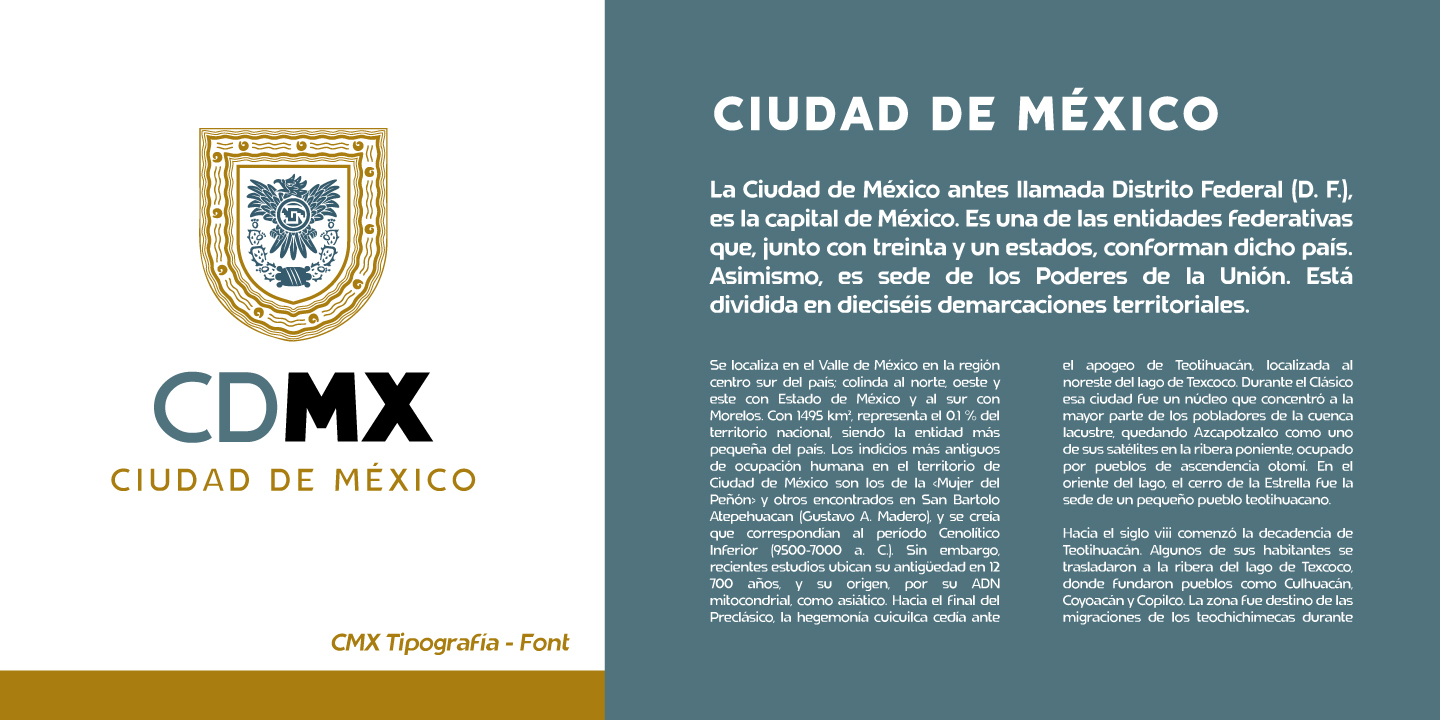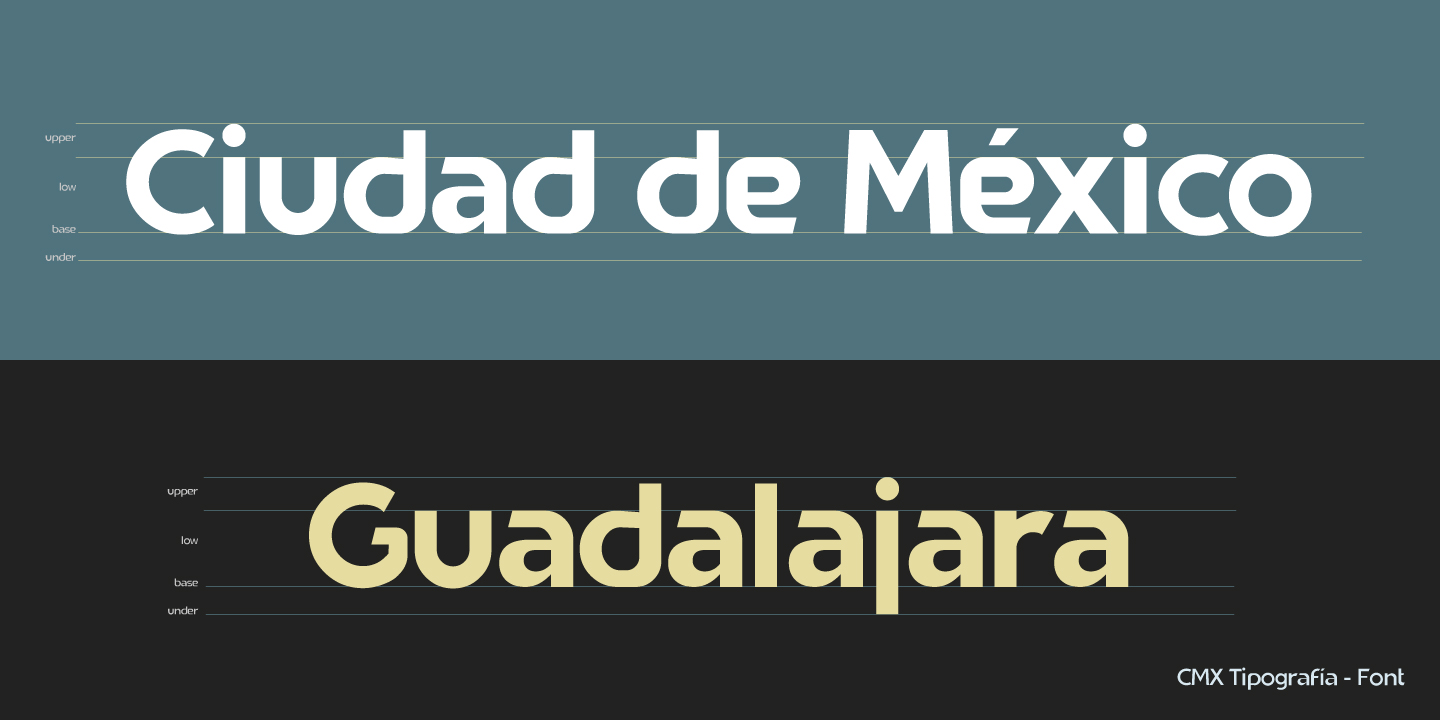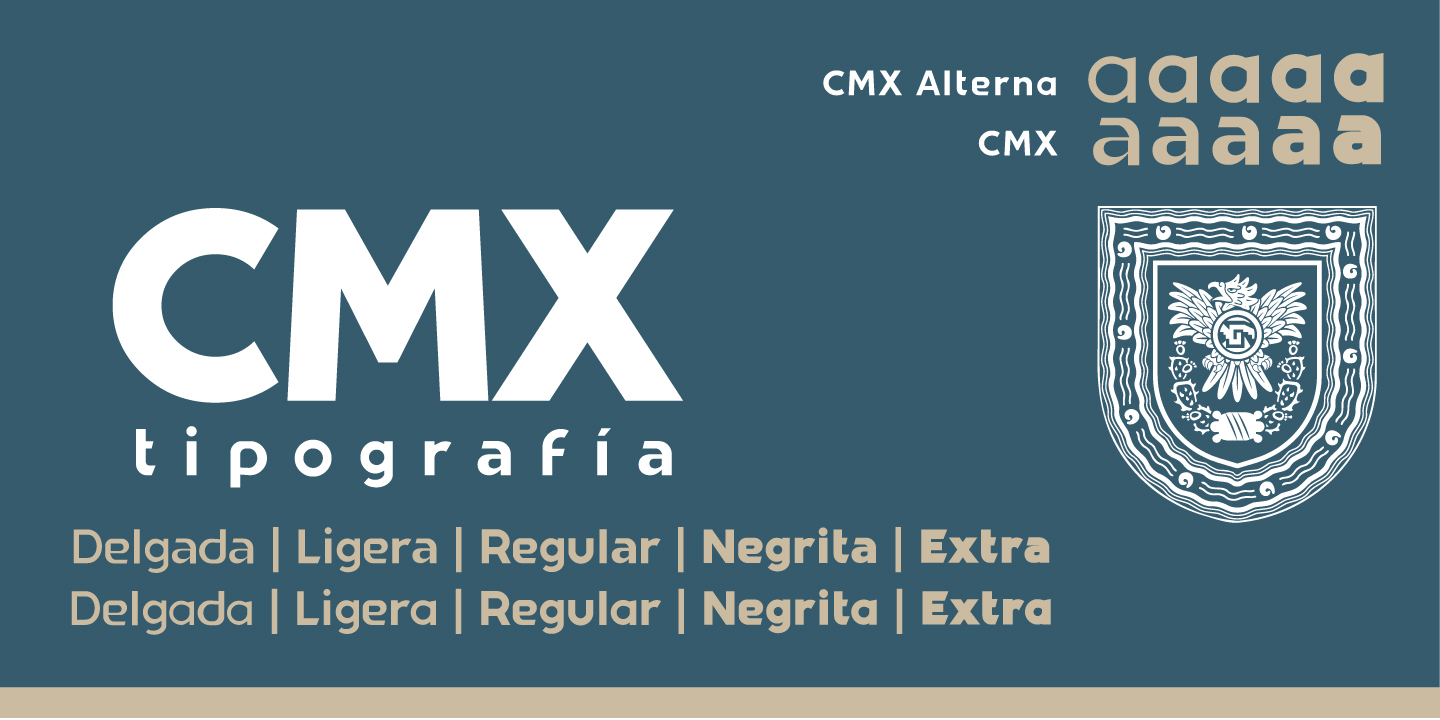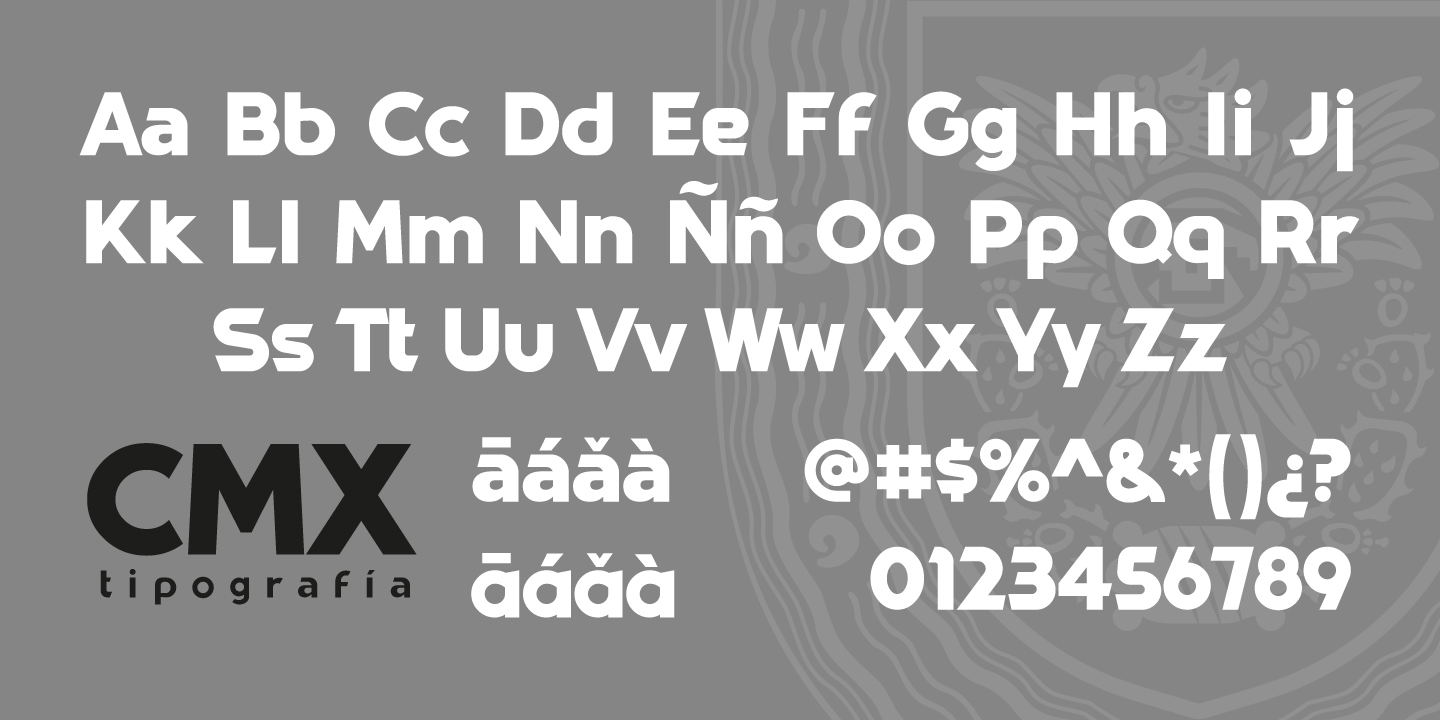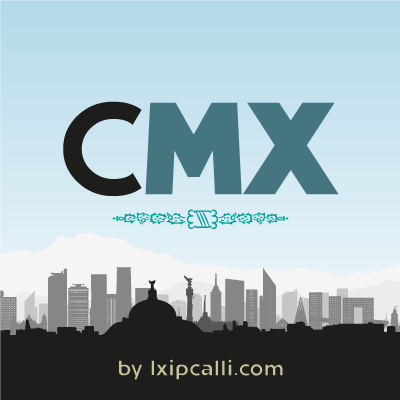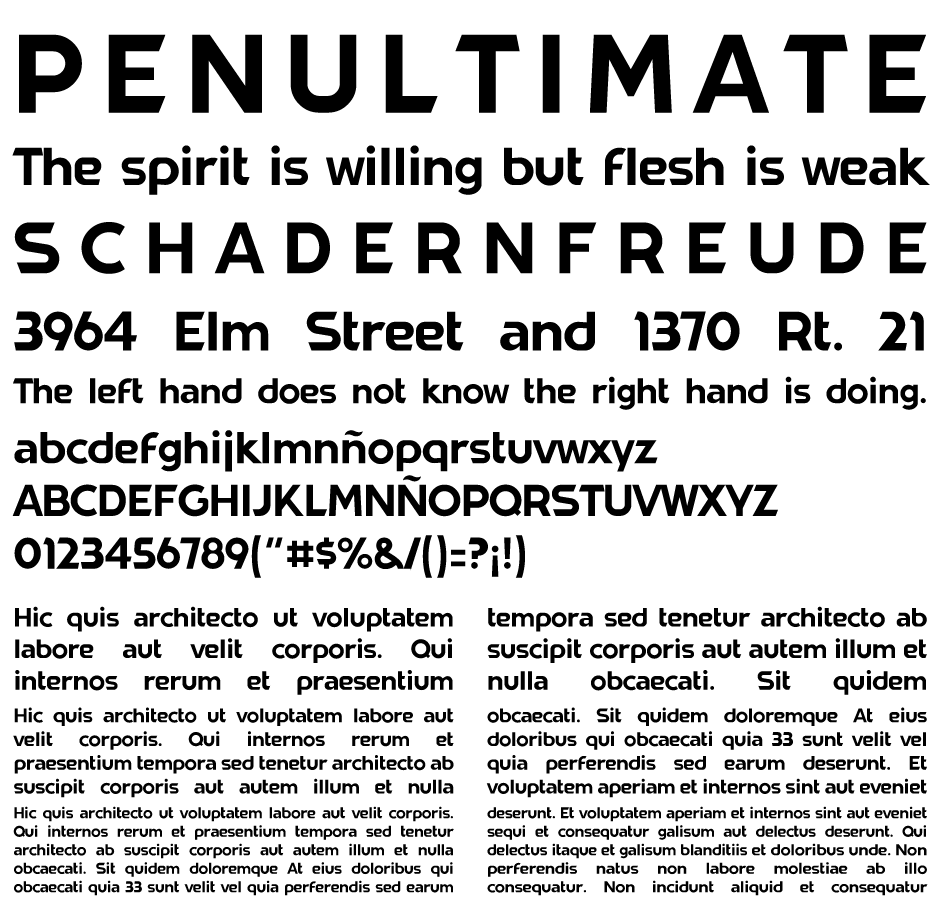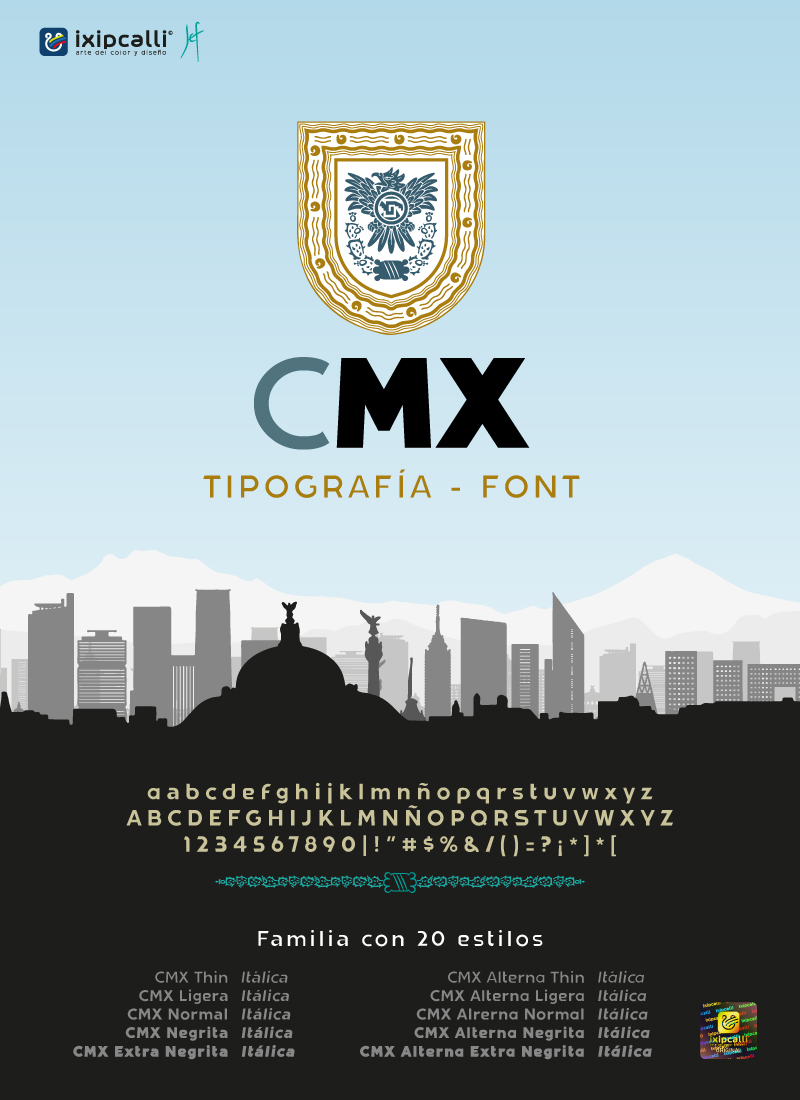
(2024) - La tipografía CMX se desarrolló como un homenaje al estilo único que define a las ciudades mexicanas, en particular a la Ciudad de México. Su nombre, CMX, significa Ciudad Mexicana y abarca no solo la Ciudad de México, sino también todas las ciudades, pueblos y municipios del país.
Esta tipografía presenta un estilo gótico sans-serif limpio y de fácil lectura. Sus caracteres ofrecen dos tipos de uso: formal e informal. Consta de veinte estilos, divididos en formas normal y de libro. Cada estilo incluye cinco grosores: Delgado, Ligero, Regular, Negrita y Extra Negrita, con su correspondiente versión en cursiva.
Esta tipografía es ideal para cualquier aplicación de diseño gráfico, especialmente para señalización, imagen corporativa y publicaciones donde se requiere resaltar texto de gran tamaño.